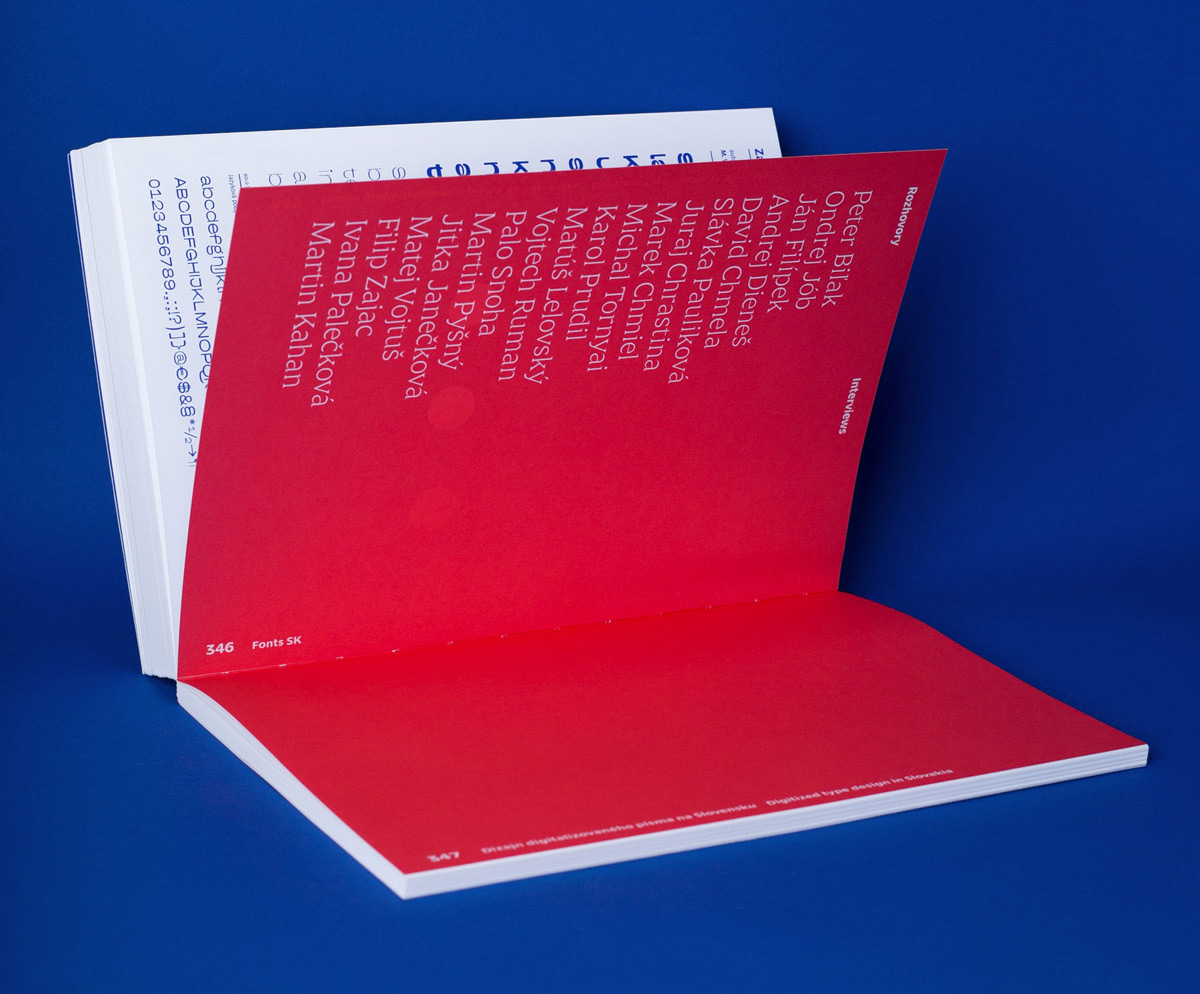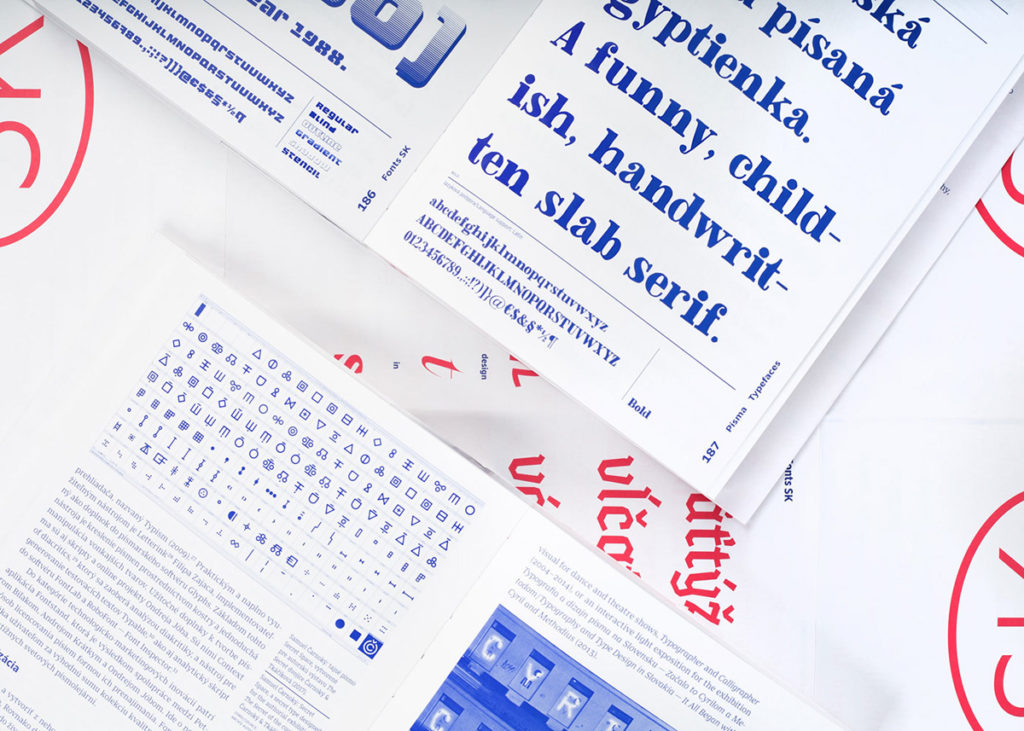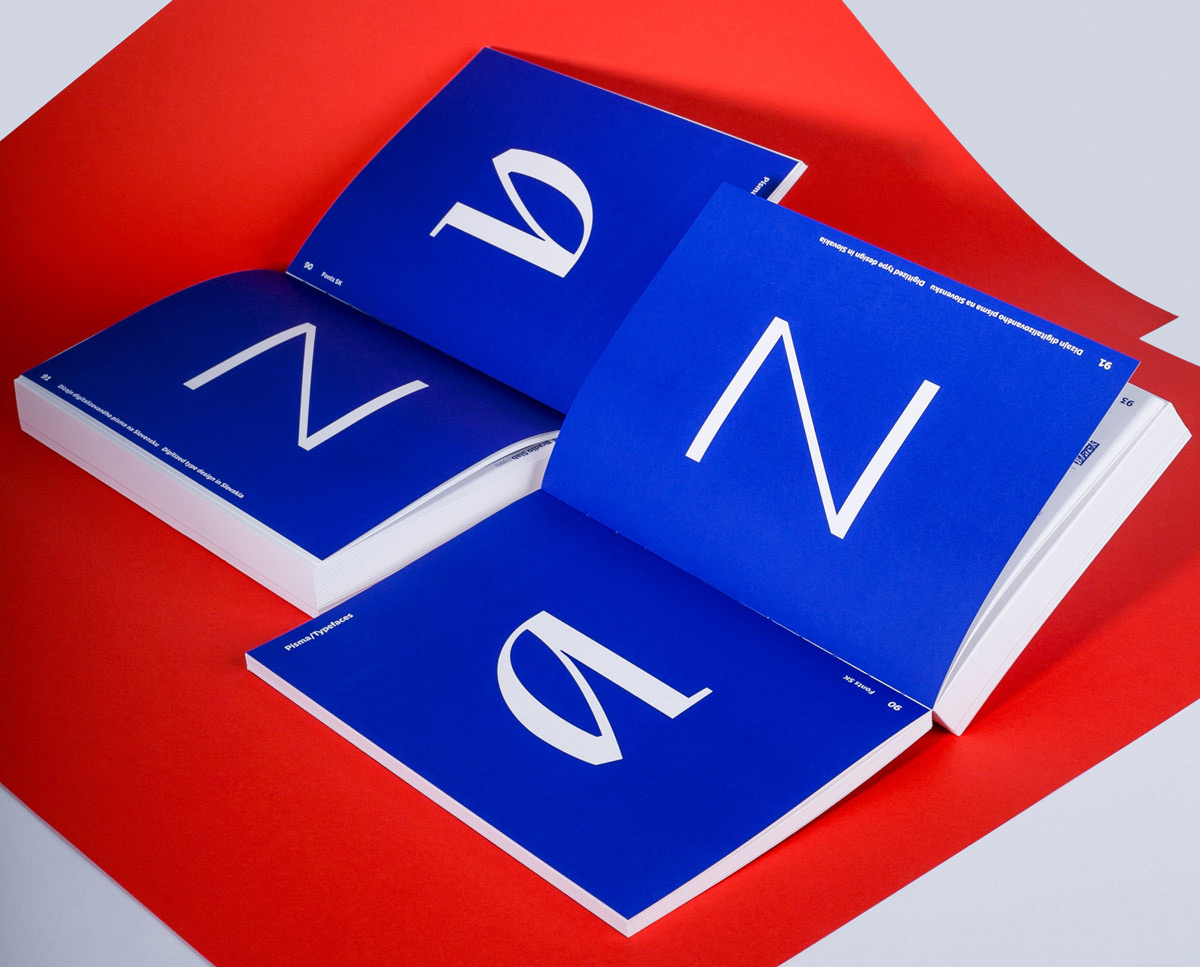
Fonts SK
Samuel Čarnoký
Slovenský designer a typograf Samuel Čarnoký vydal knihu Fonts SK. Ve více než 400 stránkové publikaci mapuje tvorbu digitálních písem na Slovensku. Kromě řady ukázek v ní najdete i rozhovory se současnými slovenskými typografy a designery.
Slovenská typografie se v posledních letech propracovala na velmi solidní úroveň a může se pochlubit i řadou špičkových designerů, kteří uspěli i v zahraničí.
„Popisuje časový záber od pionierskych začiatkov v deväťdesiatych rokoch minulého storočia až po súčasnosť. Zároveň odkazuje na historické súvislosti ako možný zdroj inšpirácie. Mapuje akademické prostredie a možnosti vzdelávania, poukazuje aj na spôsoby prezentácie a popularizácie a upozorňuje na eventuality uplatnenia písiem v praxi, “ říká autor Samuel Čarnoký.
Největší část knihy zabírají ukázky písem — ty jsou chronologicky seřazeny od roku 1988 (písmo Nara Andreje Krátkého) po současnost (písmo Zaum). Knihu doplňující rozhovory s téměř dvacítkou slovenských tvůrců písem. Obal knihy pak tvoří oboustranný plakát s ukázkami písem designerů obsažených v knize.
Koho v knize najdete?
Martin Bajaník, Andrej Barčák, Martin Benka, Peter Biľak, Johanna Biľak-Balušíková, Ladislav Csáder, Andrej Čanecký, Samuel Čarnoký, Lukáš Čeman, David Chmela, Marek Chmiel, Juraj Chrastina, Michal Chrastina, Mirka Chrastinová, Andrej Dieneš, Emil Drličiak, Jakub Dušička, Matúš Ďurčík, Martin Fek, Ján Filípek, Aurélia Garová, Ondrej Gavalda, Barbora Gavláková, Igor Imro, Kristína Jandová, Jitka Janečková, Richard Janešík, Eva Jenčuráková, Ondrej Jób, Sláva Jevčinová, Martin Kahan, David Kalata, Peter Kocúr, Lukáš Kollár, Andrej Krátky, Matúš Lelovský, Rudolf Letko, Juraj Linzboth, Jakub Mašita, Daniel Markovič, Lucia Mlynčeková, Ester Nemcová, Kristína Novosadová, Jozef Ondrík, Ivana Palečková, Jana Papierniková, Slávka Pauliková, Boris Prexta, Karol Prudil, Martin Pyšný, Vojtech Ruman, Palo Snoha, Juraj Sukop, Ján Šicko, Lucia Šohajdová, Martin Šútovec, Michal Tornyai, Jozef Tušan, Zuzana Uhalová, Miloš Vida, Matej Vojtuš, Zuzana Wohlfahrt-Senteliková, Filip Zajac.